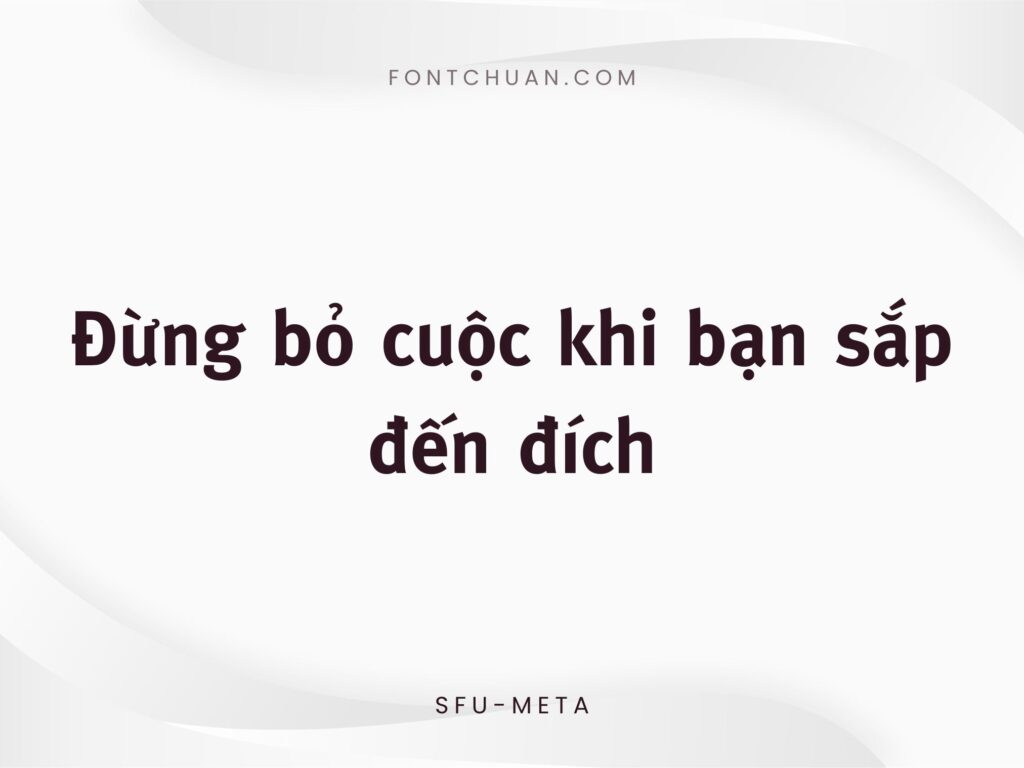
Meta là một Font Sans serif hiện đại được thiết kế bởi Erik Spiekermann vào năm 1991. Ban đầu, nó được phát triển cho Deutsche Bundespost (Bưu điện Liên bang Đức) nhưng sau đó nhanh chóng trở thành một trong những phông chữ nổi tiếng nhất của Spiekermann, có ảnh hưởng lớn đến thiết kế chữ trong nhiều thập kỷ tiếp theo. Với thiết kế tinh tế, hiện đại và khả năng ứng dụng cao, Meta đặc biệt phù hợp khi sử dụng làm Font logo trong các dự án thương hiệu, mang lại cảm giác chuyên nghiệp và ấn tượng.
Về mặt thiết kế, Meta nổi bật với chiều cao x lớn, các khoảng mở rộng và chữ “l” có đuôi giúp phân biệt rõ ràng với số “1” hoặc chữ “I” hoa, tăng cường khả năng đọc. Font này hỗ trợ nhiều ngôn ngữ và bao gồm các ký tự đặc biệt, giúp người dùng dễ dàng tùy chỉnh theo nhu cầu. Meta thường được sử dụng trong các thiết kế nhận diện thương hiệu, biển hiệu, in ấn và truyền thông kỹ thuật số. Các ngành nghề như quảng cáo, công nghệ, giáo dục và bất động sản có thể tận dụng kiểu chữ này để tạo dấu ấn đặc biệt trong truyền thông.